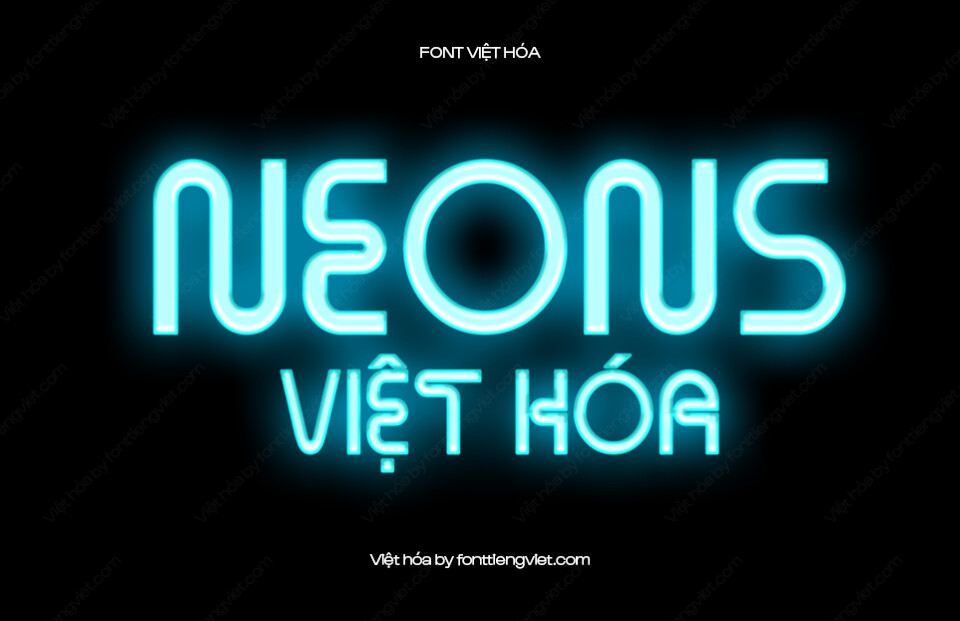
Font Việt hóa 1FTV VIP Neons
Tải Font Việt hóa 1FTV VIP Neons Miễn Phí Đỉnh Cao Cho Thiết Kế
Chào mừng các bạn học sinh và giáo viên đến với thế giới sáng tạo đầy màu sắc. Nếu bạn đang tìm kiếm một bộ Font Miễn Phí có khả năng thắp sáng mọi ý tưởng thì Font Việt hóa 1FTV VIP Neons chính là lựa chọn không thể bỏ qua. Đây là một bộ font chữ nghệ thuật được thiết kế dựa trên phong cách đèn neon rực rỡ, mang lại cảm giác hiện đại và năng động cho các dự án trình bày hay làm báo tường kỹ thuật số.
Tại sao nên chọn Font Việt hóa 1FTV VIP Neons cho giáo dục?
Thiết kế độc đáo và hiện đại
Bộ Font Việt hóa 1FTV VIP Neons sở hữu các đường nét tròn trịa và hiệu ứng phát sáng đặc trưng của bảng hiệu về đêm. Trong môi trường học đường, font chữ này giúp các tiêu đề bài thuyết trình PowerPoint trở nên thu hút hơn bao giờ hết. Sự kết hợp giữa phong cách cổ điển và công nghệ mới giúp học sinh dễ dàng tiếp cận với tư duy thiết kế hình ảnh sáng tạo.
Khả năng hiển thị tiếng Việt hoàn hảo
Điểm mạnh nhất của phiên bản này là đã được tối ưu hóa đầy đủ các dấu câu tiếng Việt. Bạn sẽ không còn gặp lỗi hiển thị khó chịu khi soạn thảo nội dung. Font Việt hóa 1FTV VIP Neons giúp mọi thông điệp của nhà trường và học sinh được truyền tải một cách trọn vẹn, thẩm mỹ và chuyên nghiệp trên mọi nền tảng đồ họa thông dụng hiện nay.
Cách ứng dụng Font Việt hóa 1FTV VIP Neons hiệu quả
Để tận dụng tối đa vẻ đẹp của bộ font này, các bạn nên sử dụng trên nền tối để tạo hiệu ứng tương phản mạnh mẽ nhất. Đây là công cụ đắc lực để thiết kế poster sự kiện trường học, bìa sổ tay hoặc các banner chào mừng. Hãy bắt đầu trải nghiệm Font Miễn Phí, Font Việt Hóa, Font Việt hóa 1FTV VIP Neons ngay hôm nay để biến những bài học khô khan thành những tác phẩm nghệ thuật ánh sáng đầy cảm hứng nhé.